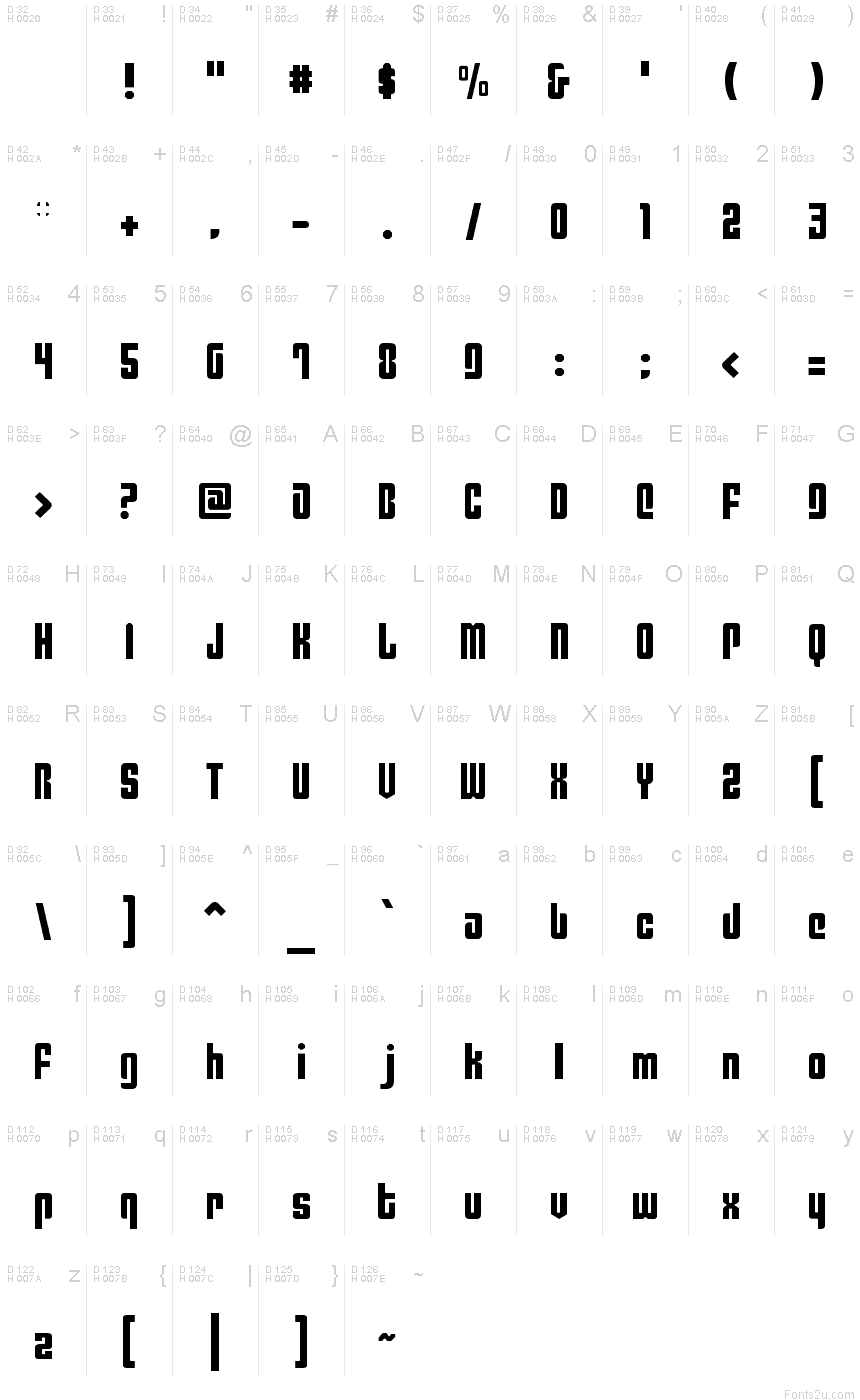
Philadelphia Light von Iconian Fonts ist eine kostenlose, moderne Display-Schrift mit einem scharfen retro-futuristischen Charakter. Die Buchstaben wirken hoch und urban: konstruiert aus geraden Vertikalen und kantigen Ecken, die durch weiche Rundungen und tiefe Einschnitte abgemildert werden. Das verleiht dem Design einen eleganten Rhythmus im Stil alter Plakate.
Sie eignet sich perfekt für das Branding von Musik-Events, Nachtleben-Flyern, Spieltiteln, Tech-Verpackungen und Magazin-Überschriften, bei denen eine stilisierte Skyline-Ästhetik das Konzept unterstützt. Als kostenlose Schrift macht sie sich auch hervorragend für kurze Titelkarten, Monogramme und Logo-Skizzen, da die schmalen Schäfte und blockartigen Kurven selbst einzelne Buchstaben grafisch und eigenständig wirken lassen.
Philadelphia Light